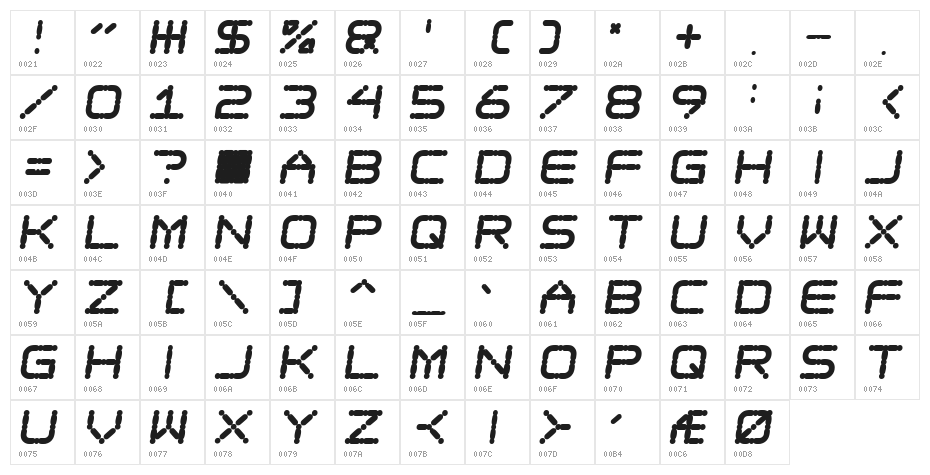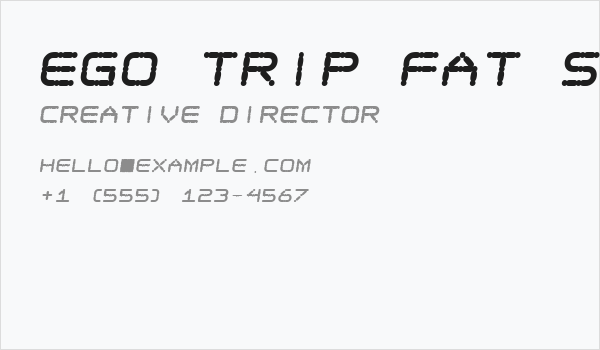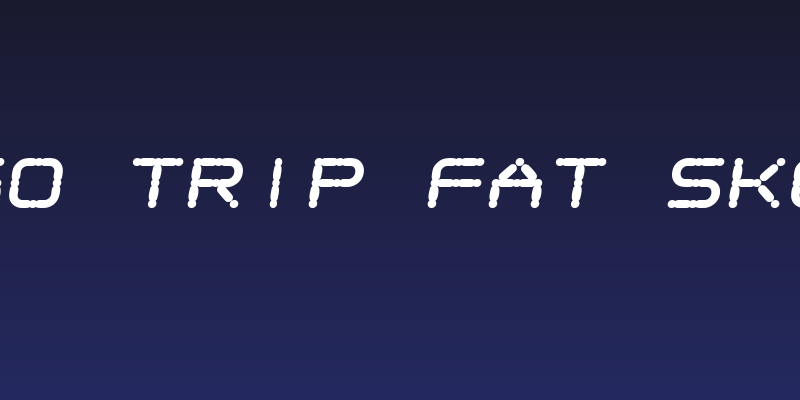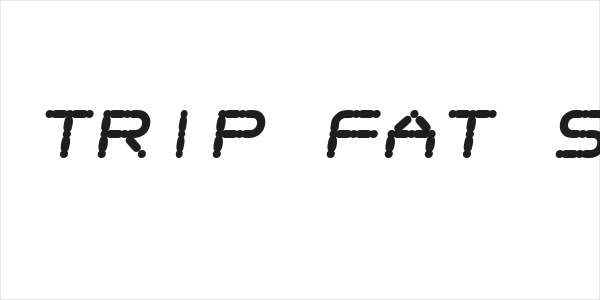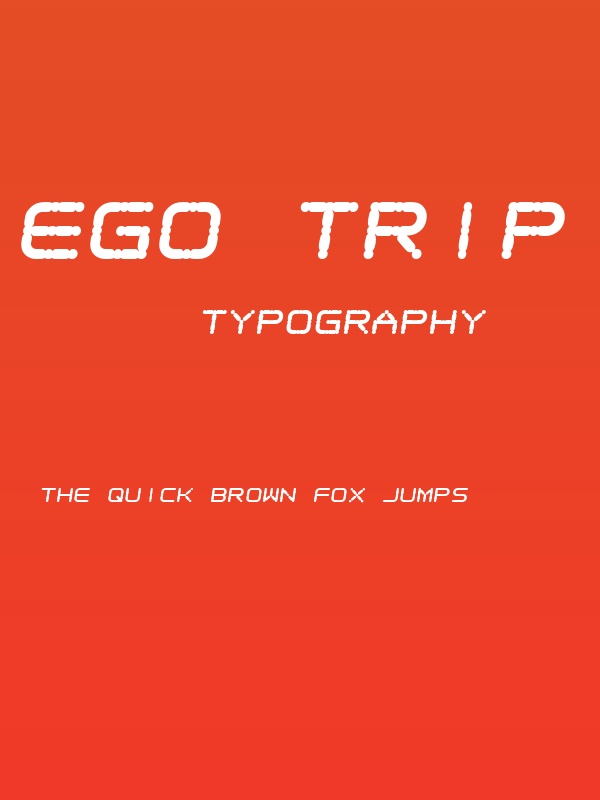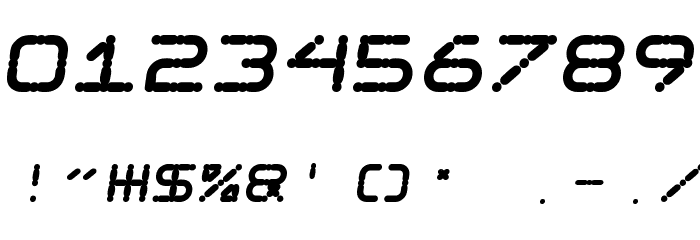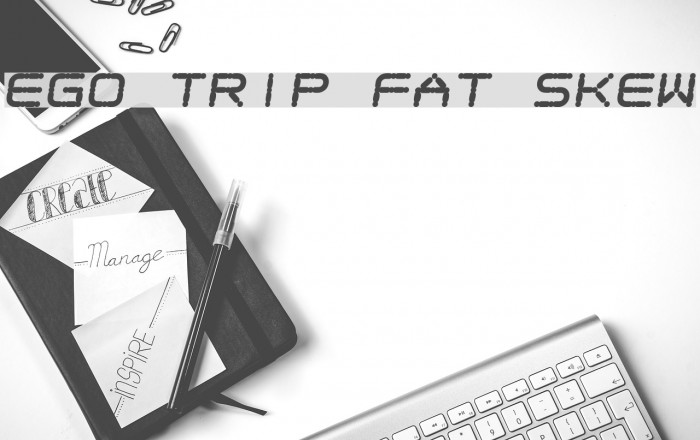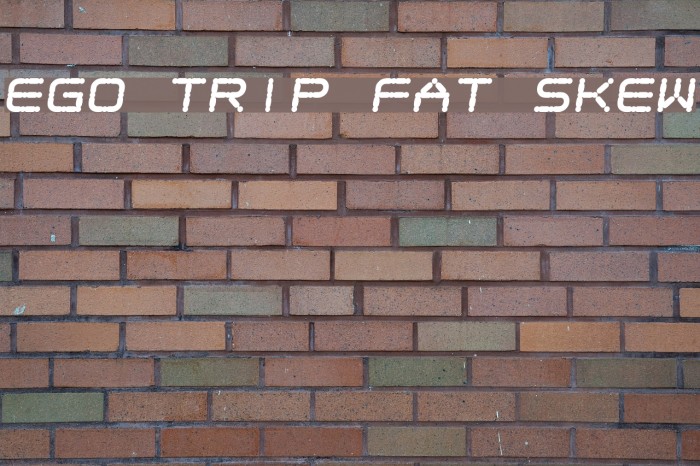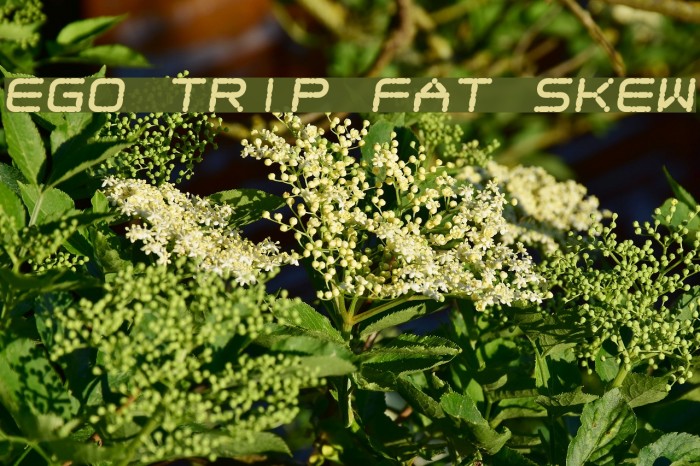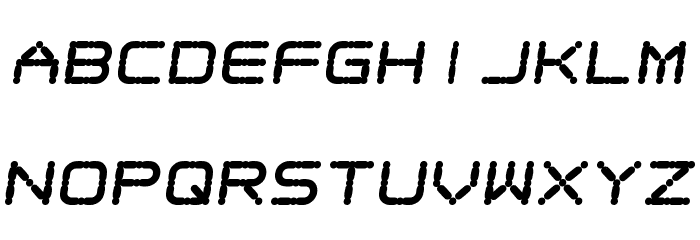
Ego trip Fat Skew Font
| Categorías | Capitals |
| Proyectos propuestos | Ideal for technology branding, digital art projects, video game interfaces, and futuristic-themed posters. |